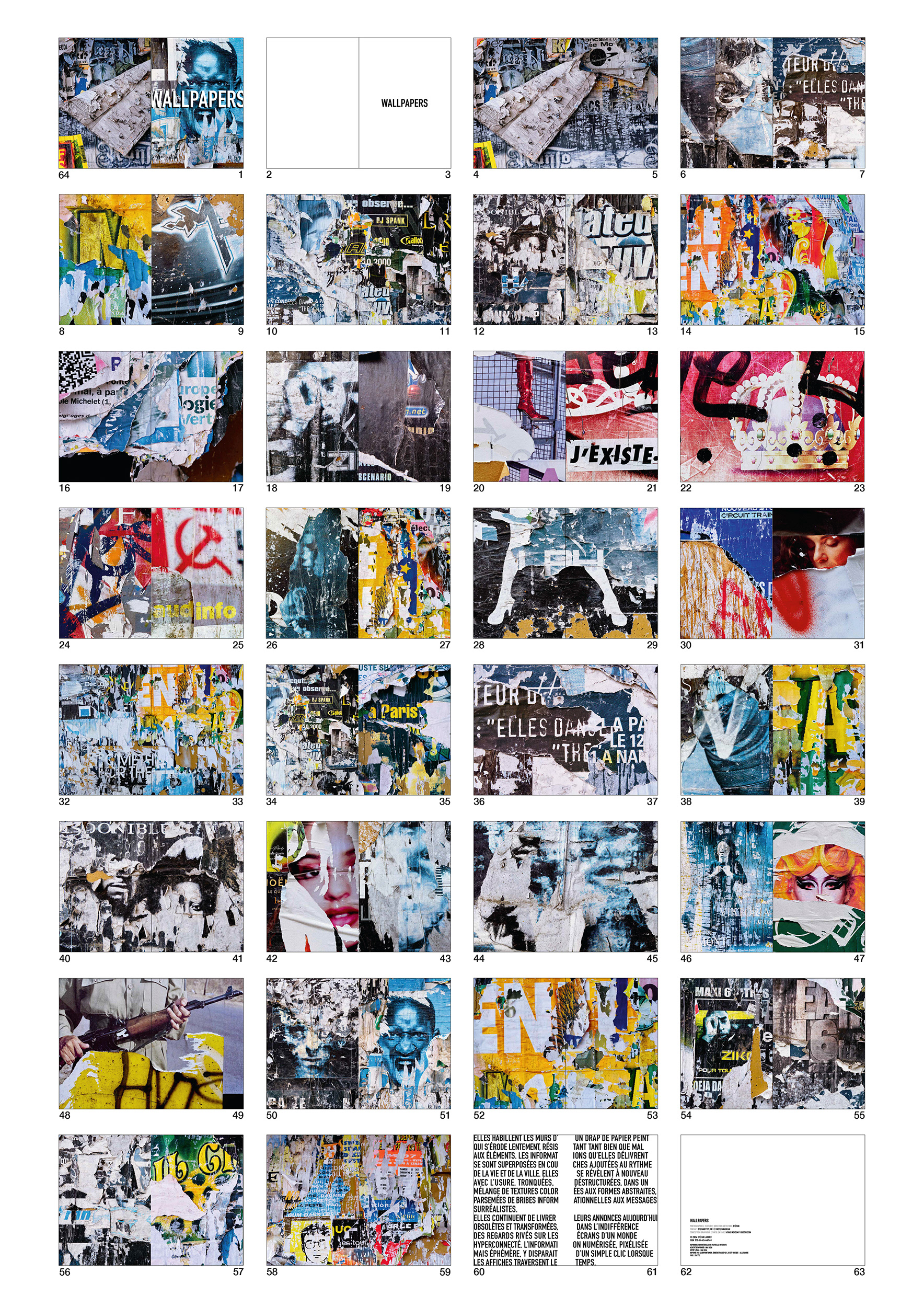
Un livre auto-édité, dans un esprit "do it yourself".
Il compile des photographies d'affiches tapissant les murs de la ville qui en se détériorant, créent un mélange de textures, de couleurs et de bribes de textes. Une ambiance de fin du monde, ou post-apocalyptique s’en dégage. Il y a comme un décalage entre l’aspect analogique de ces affiches usées par le temps, et l’information numérique dans un monde hyper connecté, qui disparait d’un simple clic.
Avec ces couches de papiers déstructurées et chaotiques, c’est cette esthétique vintage, un peu punk, voire grunge, qui touche ma sensibilité et mon regard d’ex ado des 80’s.